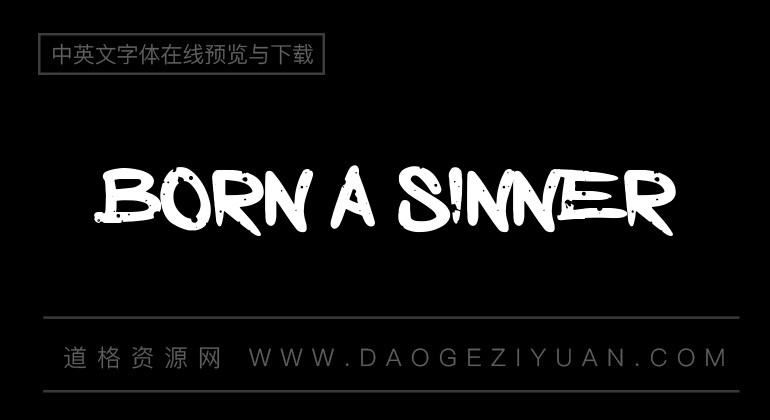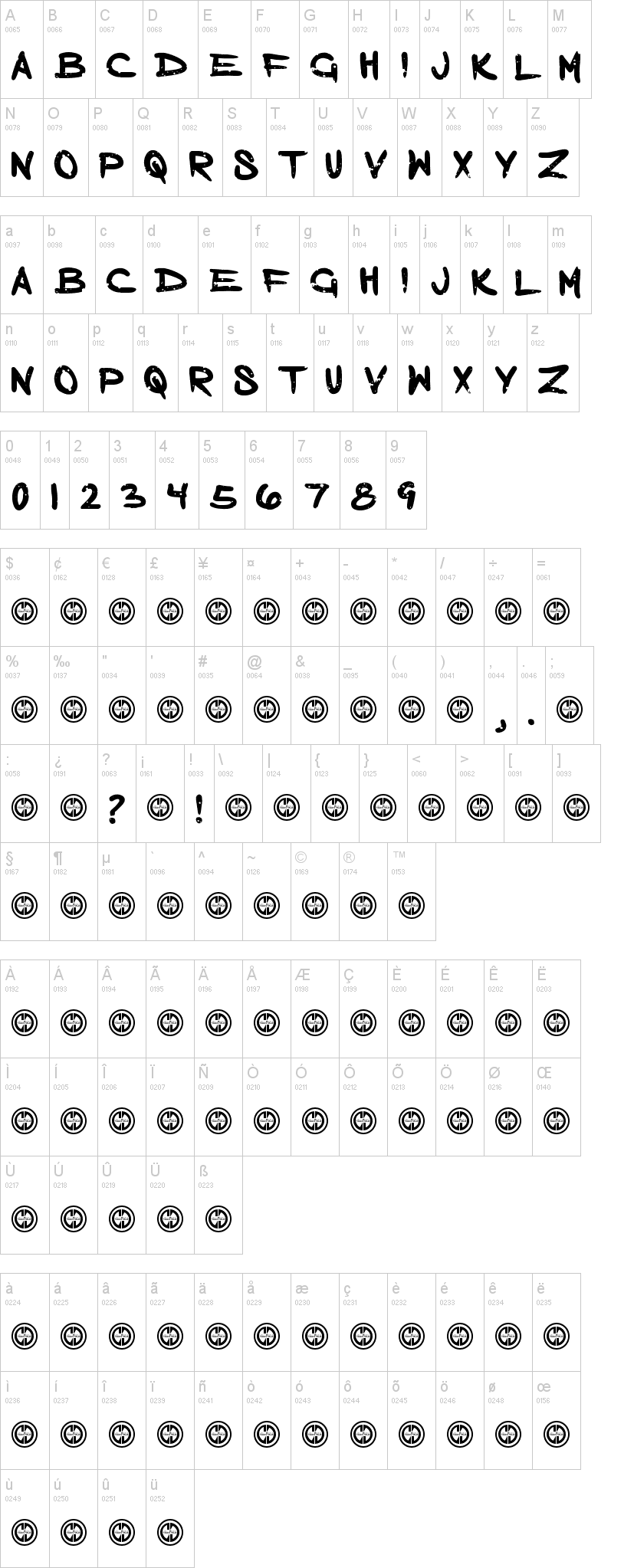
Born a Sinner
Born a Sinner 是一款英文字体,它是由一位叫做Konstantine Studio的设计师所设计的。Born a Sinner字体具有粗犷、鲜明、极具个性的特点,适合用于标题、标识、海报、T恤等等的设计。它的字体设计灵感来源于20世纪60年代的西部文化,有着鲜明的西部风格。它的字形设计比较粗犷,拥有丰富的表现形式,可以满足多种设计需求。
Born a Sinner是一款非常不错的手写艺术字体,具有很好的视觉感,适合于文化类的宣传设计、商业类品牌的广告和产品包装设计以及个性化文字排版等较多场景。